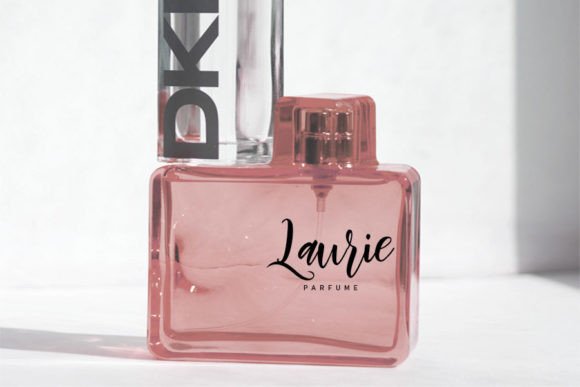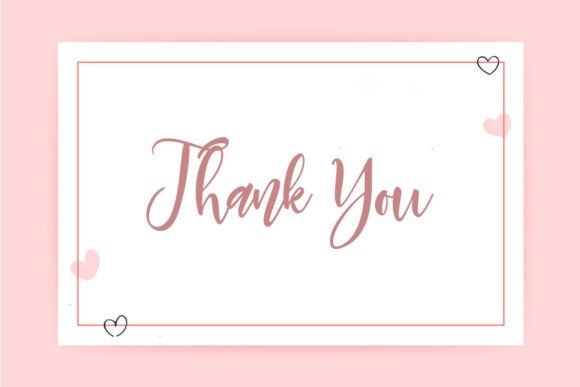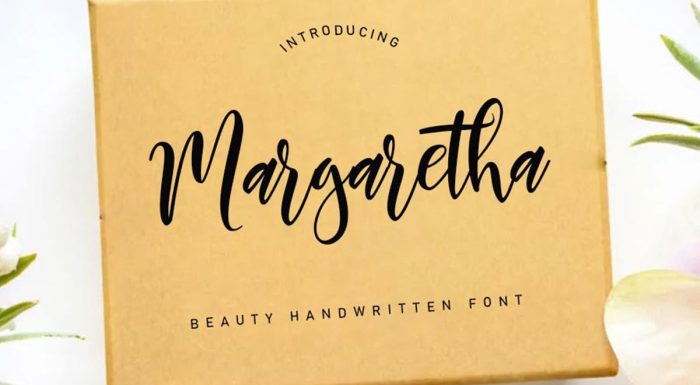
فونت Margaretha انگلیسی
دانلود فونت Margaretha انگلیسی Font مارگارتا |
| ⭐ مجموعه فونت | دانلود فونت انگلیسی مارگارتا Font Margaretha |
| ⭐ توضیحات | مارگارتا فونت را معرفی می کنیم، خطی برازنده و رسا و حروف دست نویسی که مظهر ظرافت و جذابیت است. این فونت با خطوط روان و منحنی های ظریف خود، حسی از پیچیدگی را به طرح های شما می بخشد. فونت مارگارتا که برای دعوتنامهها، لوگوها و پروژههای برندسازی ایدهآل است، زیبایی جاودانهای به آن اضافه میکند و با هر ضربه قلم، جوهره ظرافت دستنویس را به تصویر میکشد. |